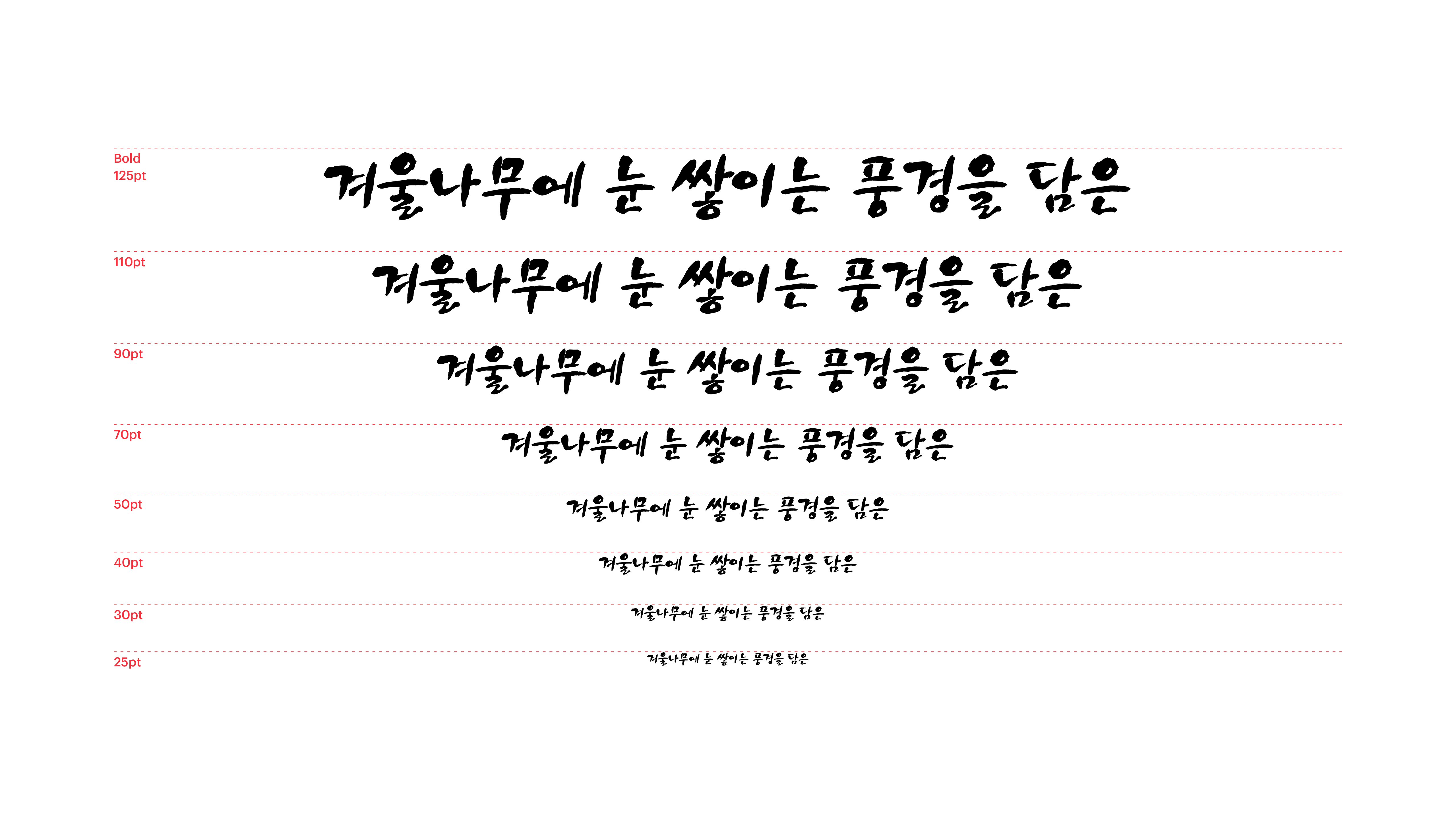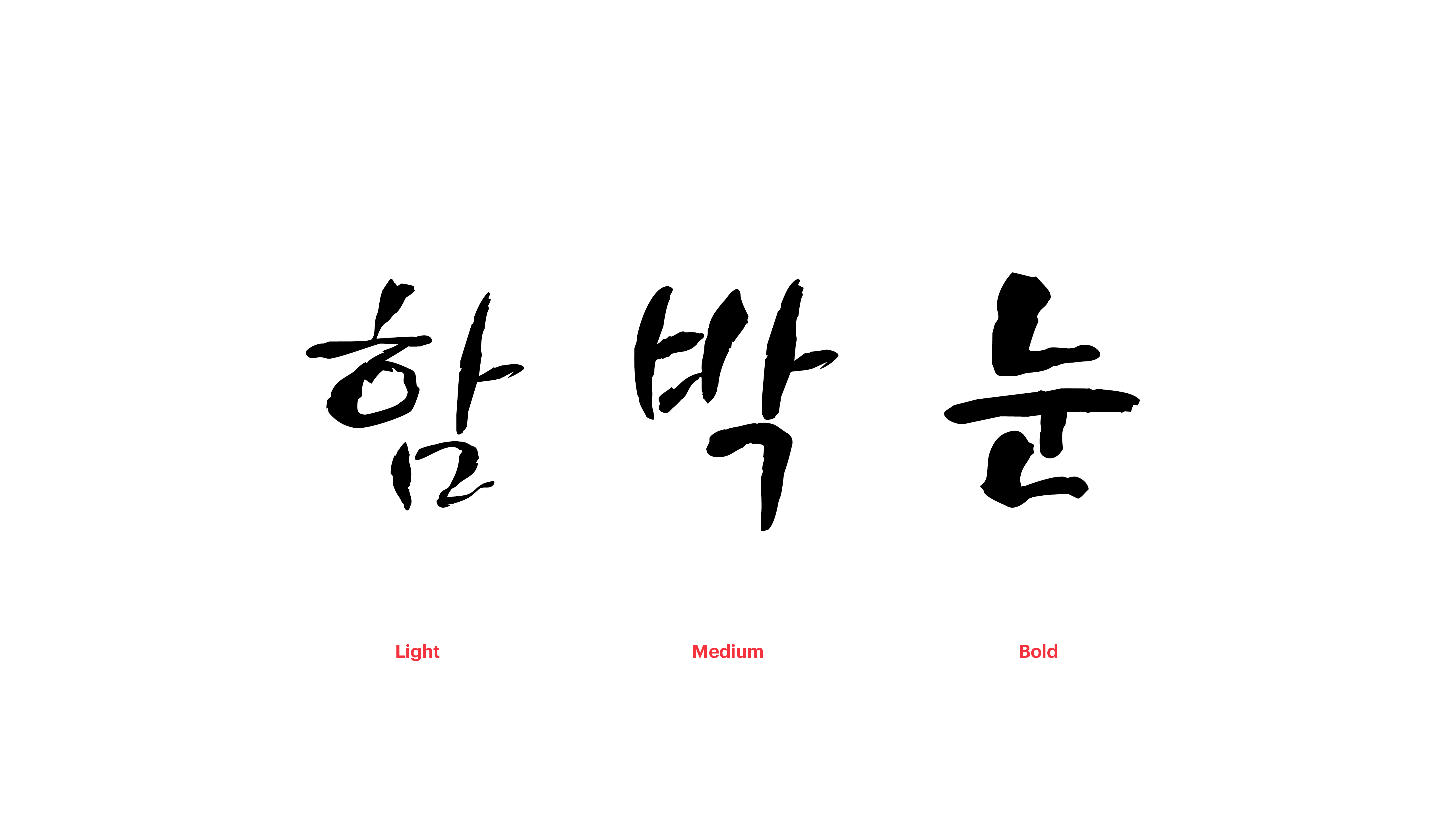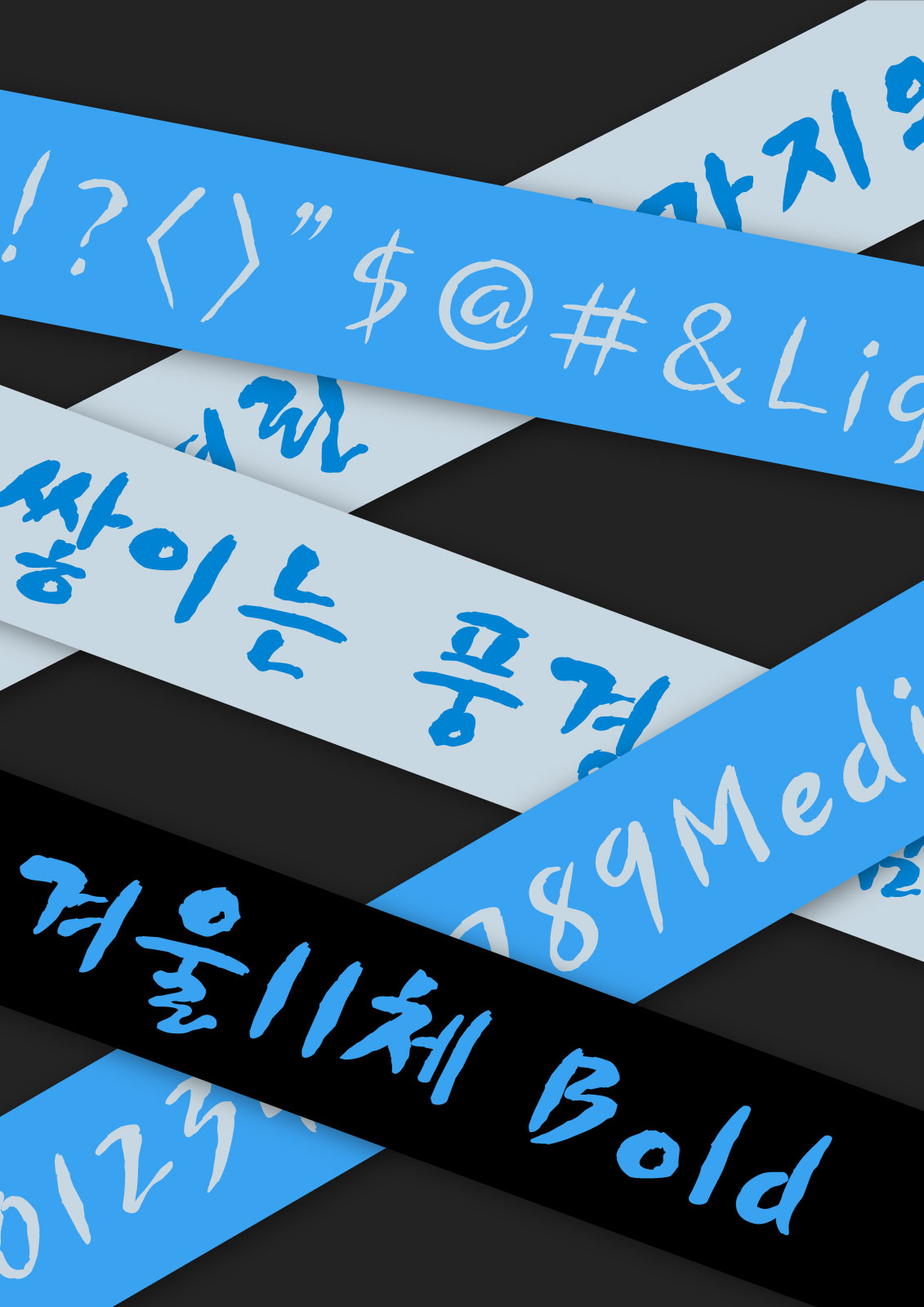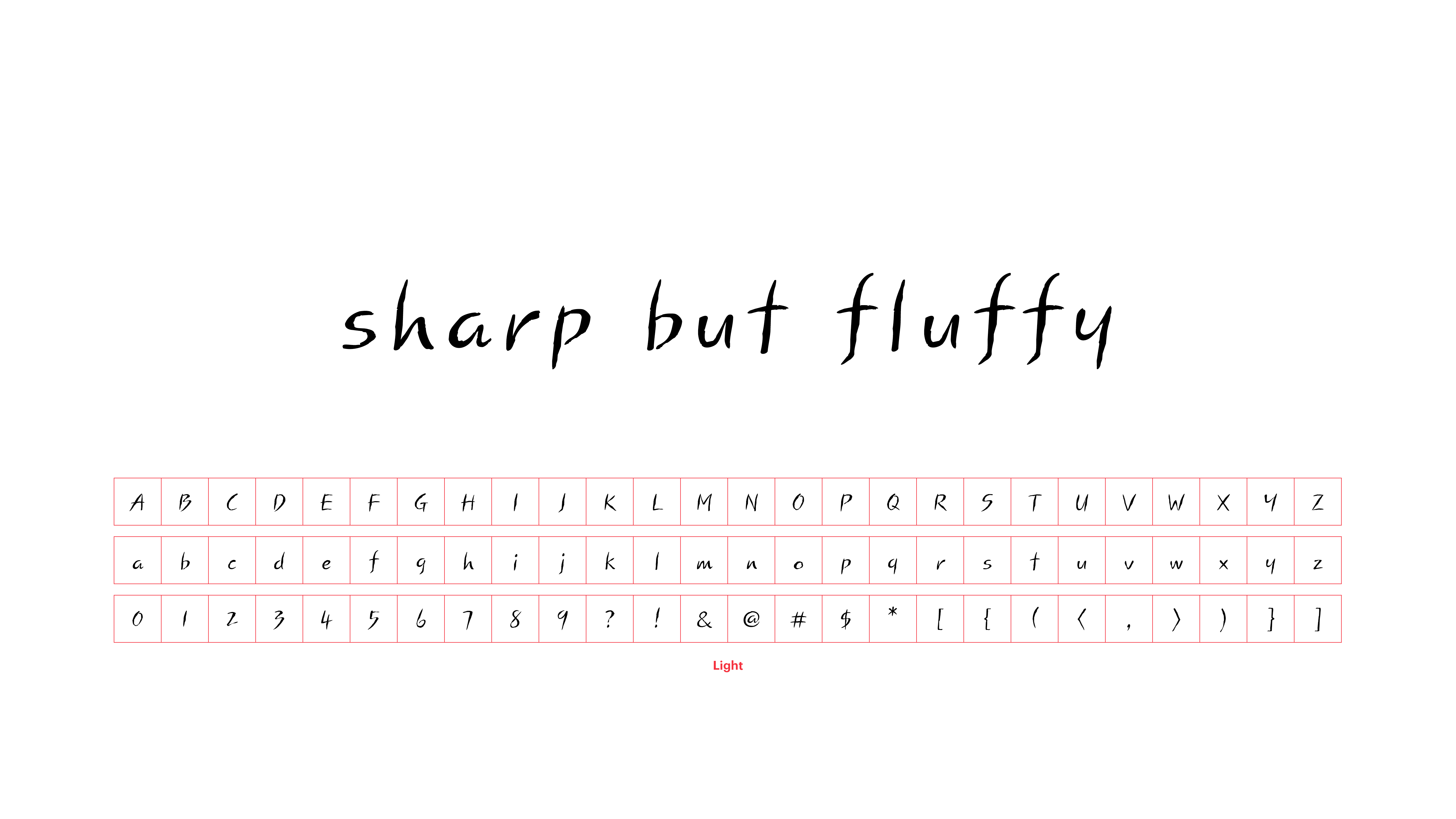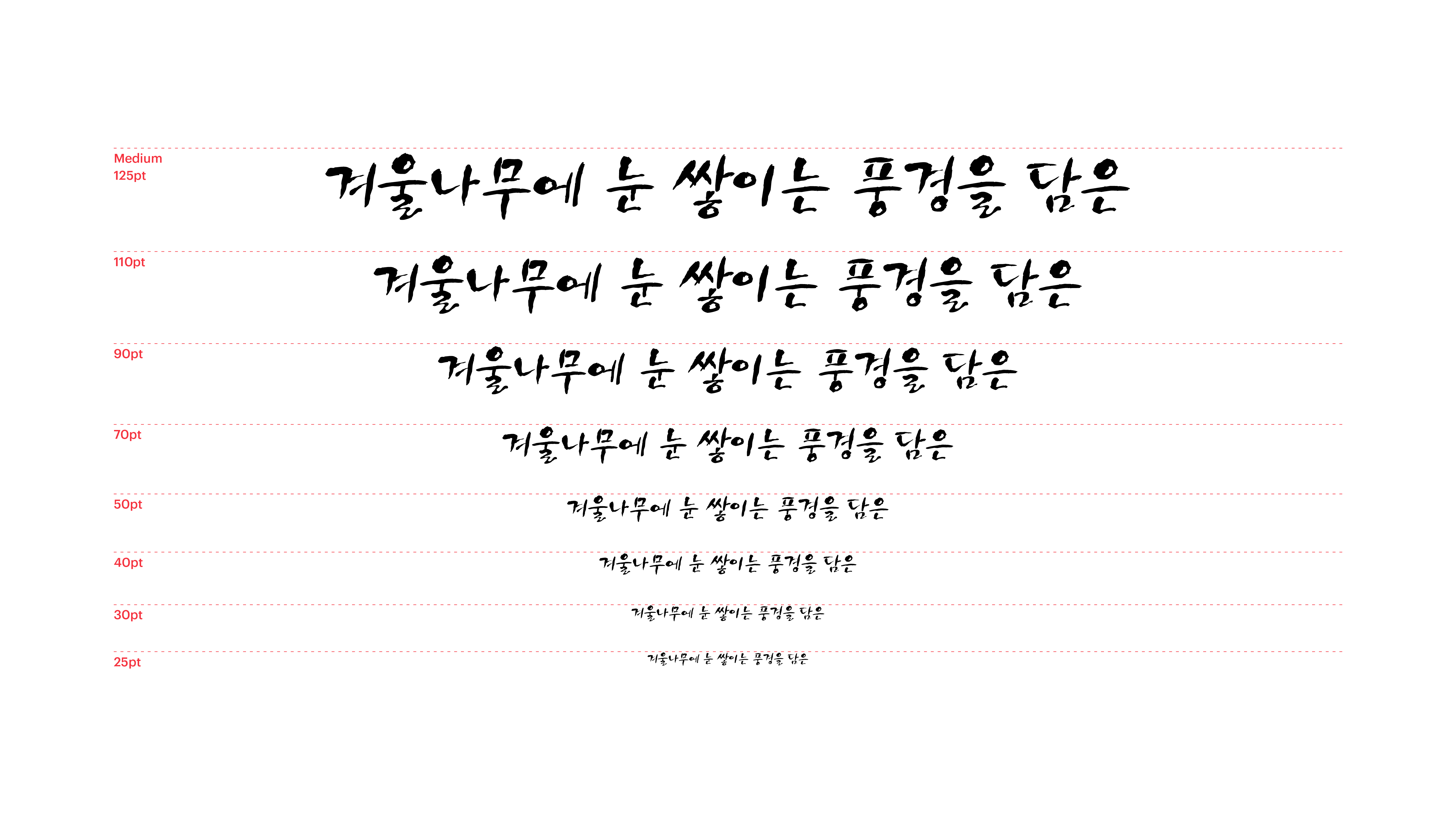
겨울II
Yoon 겨울II
겨울II체에는 겨울나무에 눈 쌓이는 풍경이 고스란히 담겨 있습니다. 가녀린 나뭇가지의 앙상한 느낌을 살린 필기체 폰트이지만, 두께를 달리하면 함박눈 쌓인 듯 포근한 감성의 연출도 가능하지요. 날카롭고 예리한 이야기부터 폭신폭신 따뜻한 이야기까지, 기나긴 겨울밤처럼 겨울II체로 쓸 수 있는 이야기도 무궁무진하답니다.